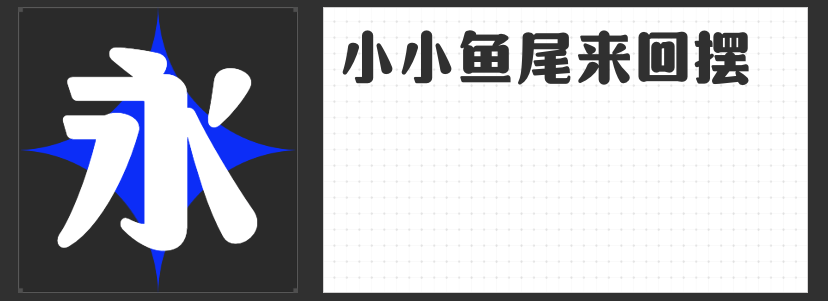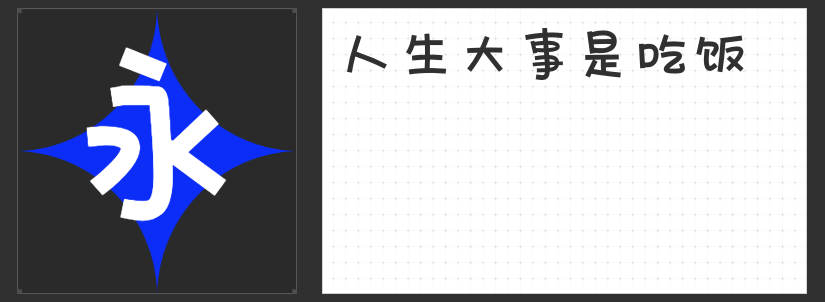
四款磅礴与灵动并存的设计利器:解锁海报标题的视觉张力
在海报设计的视觉叙事中,标题字体是传递核心情绪的第一把钥匙。一款兼具力量感与艺术性的字体,能瞬间抓住观者目光,为整体设计奠定基调。以下四款精心挑选的字体,以独特的结构美学与性格表达,成为海报标题设计的“点睛之笔”。
一、励字磅礴简 超黑
这款字体以“斜体与正体的融合”打破传统黑体的静态框架——左侧微斜的笔画注入动态韵律,右侧垂直的线条则稳固整体重心,形成“万壑争流”般的视觉张力。其设计暗合中国山水画的意境哲学,既适合科技、运动类海报的硬核表达,也能驾驭文化、艺术主题的深邃感,让标题如山峰般巍然屹立。
二、字圈也字花卷体
以中式花卷为灵感原点,这款字体将食物的柔软形态转化为几何化的硬朗结构:左低右高的倾斜姿态暗藏叛逆基因,钝角与直角的交替使用打破常规,棱角的圆润与尖锐碰撞出矛盾美感。它适合年轻化、潮流向的海报设计,无论是音乐节、创意市集还是亚文化品牌,都能通过字体的“不羁态度”与受众产生情感共鸣。
三、励字星宜简
通过圆形起落笔与拼接感笔画,这款字体将“天真”转化为可感知的视觉语言。厚重的字形中透露出手作般的温度,既保留了黑体的稳重,又融入卡通字体的灵动,尤其适合亲子、教育、文创类海报。其柔和的轮廓能弱化商业感,传递温暖、亲近的品牌气质。
四、励字光明简 超黑
以“弧线与太阳圆”为核心设计语言,这款超黑字体用饱满的笔画与开阔的字宫构建出强烈的视觉冲击力。斜切处理的横笔画与口字部设计,在厚重中注入锐利锋芒,使其既能胜任汽车、电竞等硬核领域的标题,也能通过拉伸变形适配艺术展览、时尚活动的先锋感。无线衬托的装饰性,让字体本身即成为设计主体。
从磅礴气势到童趣盎然,从叛逆锋芒到太阳图腾,这四款字体以差异化的美学语言,为海报标题设计提供了丰富的表达维度。它们不仅是文字的载体,更是视觉叙事的策略工具,助力设计师在信息洪流中打造令人过目难忘的“第一眼惊艳”。